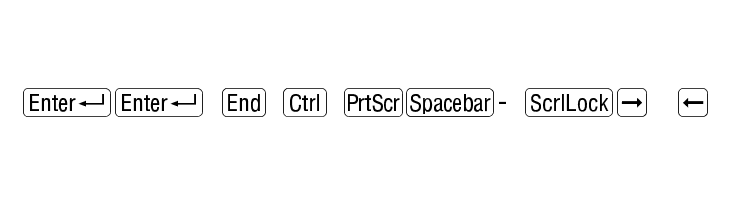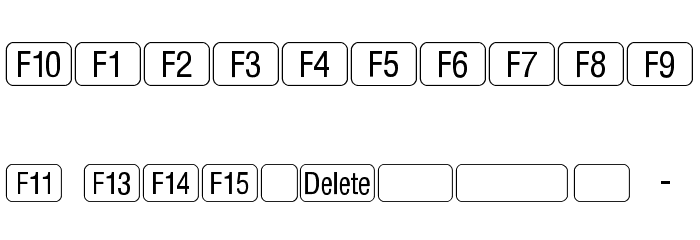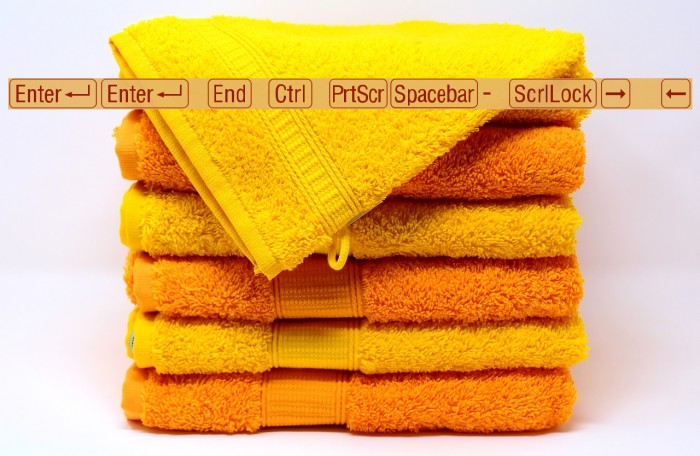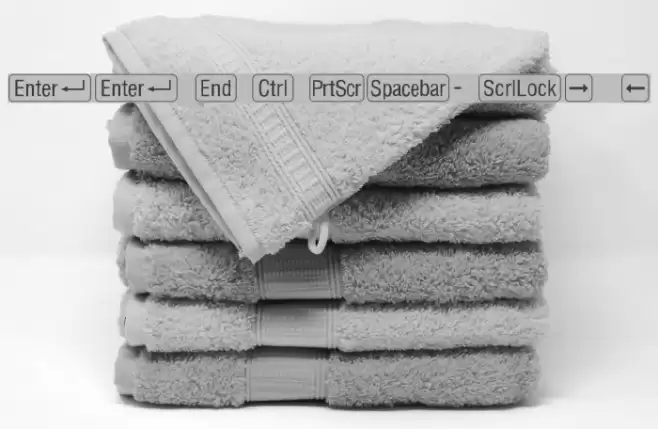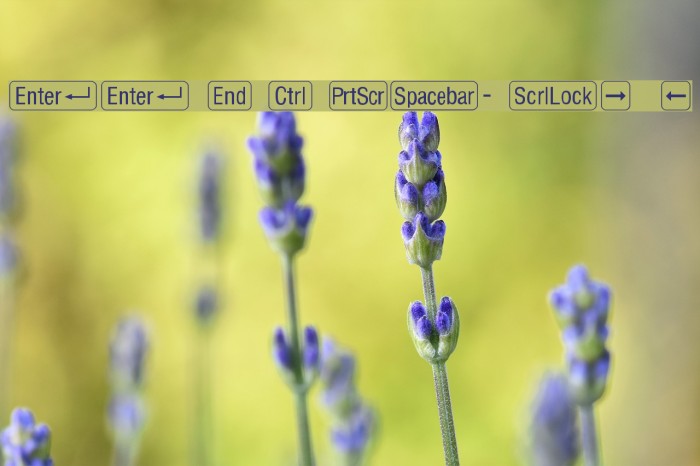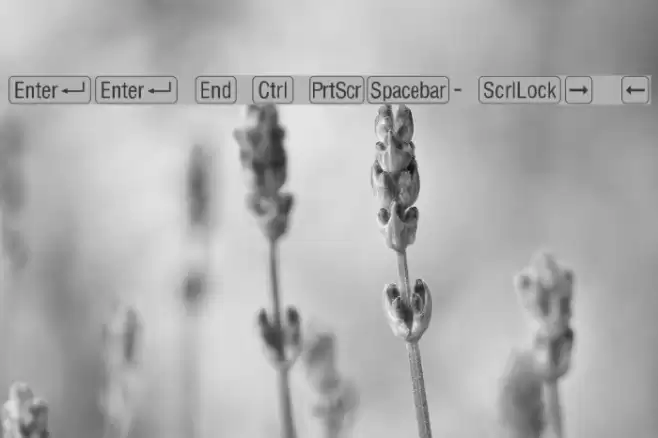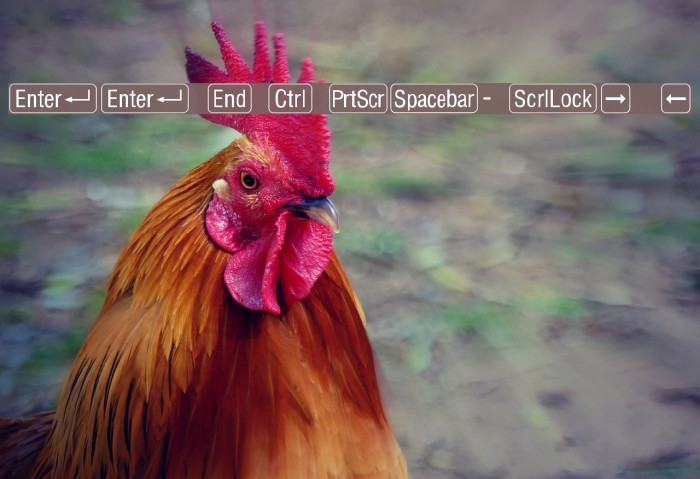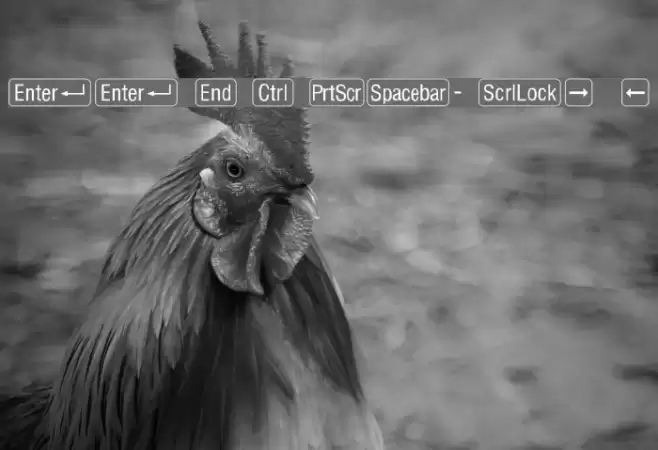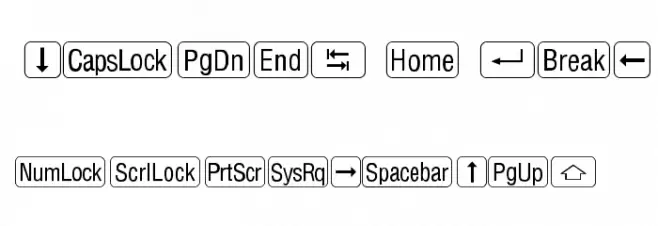
RRKeyCaps-Normal Font
| उपयोग का मामला | User interfaces, technical documentation, educational materials. |
| सुझाए गए प्रोजेक्ट | Ideal for digital interfaces, technical documentation, user manuals, and educational materials related to computing. |